UI设计中字体与排版指南,小白必看!
引言
字体与排版是UI设计中的基础元素,它们不仅影响视觉效果,还能传达信息和情感。本教程将深入探讨这2个方面,提供实用的字体与排版技巧和建议,帮助你提升设计水平。
1、UI设计中字体指南
字体分类
字体大致可以分为三类:衬线字体、无衬线字体和装饰字体。
- 衬线字体:如Times New Roman,适用于正式和传统的场合。
- 无衬线字体:如Arial,适用于现代和简约的设计。
- 装饰字体:如Comic Sans,适用于特定主题或情感。
字体匹配
字体匹配是字体与排版中一个复杂但重要的过程。以下是一些基本原则:
对比但和谐:选择的字体应该有足够的对比,以区分不同的文本元素,但也应该和谐,以创建统一的视觉效果。例如,你可以选择一种衬线字体用于标题,和一种无衬线字体用于正文。
UI设计中不超过三种字体:为了避免混乱,最好不要在一个设计中使用超过三种字体。如果确实需要多种字体,确保它们有共同的设计元素,如笔画粗细或字母形状。
字体风格和场合:在UI设计中不同的字体有不同的风格和情感,因此应根据设计的目的和场合来选择字体。例如,正式的商业报告可能更适合使用经典的衬线字体,而创意广告则可能更适合使用现代的无衬线字体。
实用技巧
字体权重和样式:在UI设计中使用不同的字体权重(粗细)和样式(斜体、下划线等)来增加层次感和强调。例如,你可以使用粗体来突出重要的关键词或短语。
测试和反馈:在确定字体选择后,最好进行一些用户测试,以确保字体易于阅读和理解。你也可以从同行或目标受众那里获取反馈,以进一步优化字体选择。
2、UI设计中排版指南
基础概念
排版是文字和图像在页面或屏幕上的布局。在UI设计中好的排版能提高阅读体验,强调重要信息,并增加视觉吸引力。
网格系统
网格系统是排版的基础,它帮助设计师在页面上创建一致和平衡的布局。网格由列、行和间距组成,可以是固定或流动的。
文字层次结构
文字层次结构是通过字体大小、粗细和颜色等手段,区分标题、副标题和正文,以引导读者的注意力。
实用技巧
对齐和间距:在UI设计中文本和元素应该沿网格线对齐,以创建整洁的外观。同时,注意元素之间的间距,避免拥挤或过于分散。具体来说,元素之间的间距应该至少为元素高度的1/8,以保持视觉平衡。
行高和字距:合适的行高和字距能提高阅读体验。一般来说,行高应为字体大小的1.5倍,字距应稍微小于字体大小。在长段落中,可以适当增加行高以提高可读性。
文本块和分栏:在UI设计中处理大量文本时,考虑使用文本块或分栏来提高可读性。文本块可以用于突出重要信息,而分栏则可以使长文本更易于阅读。
视觉焦点和信息层次:通过使用不同大小和颜色的字体,以及添加图像或图标,你可以创建UI设计的视觉焦点和信息层次,从而引导读者的注意力。
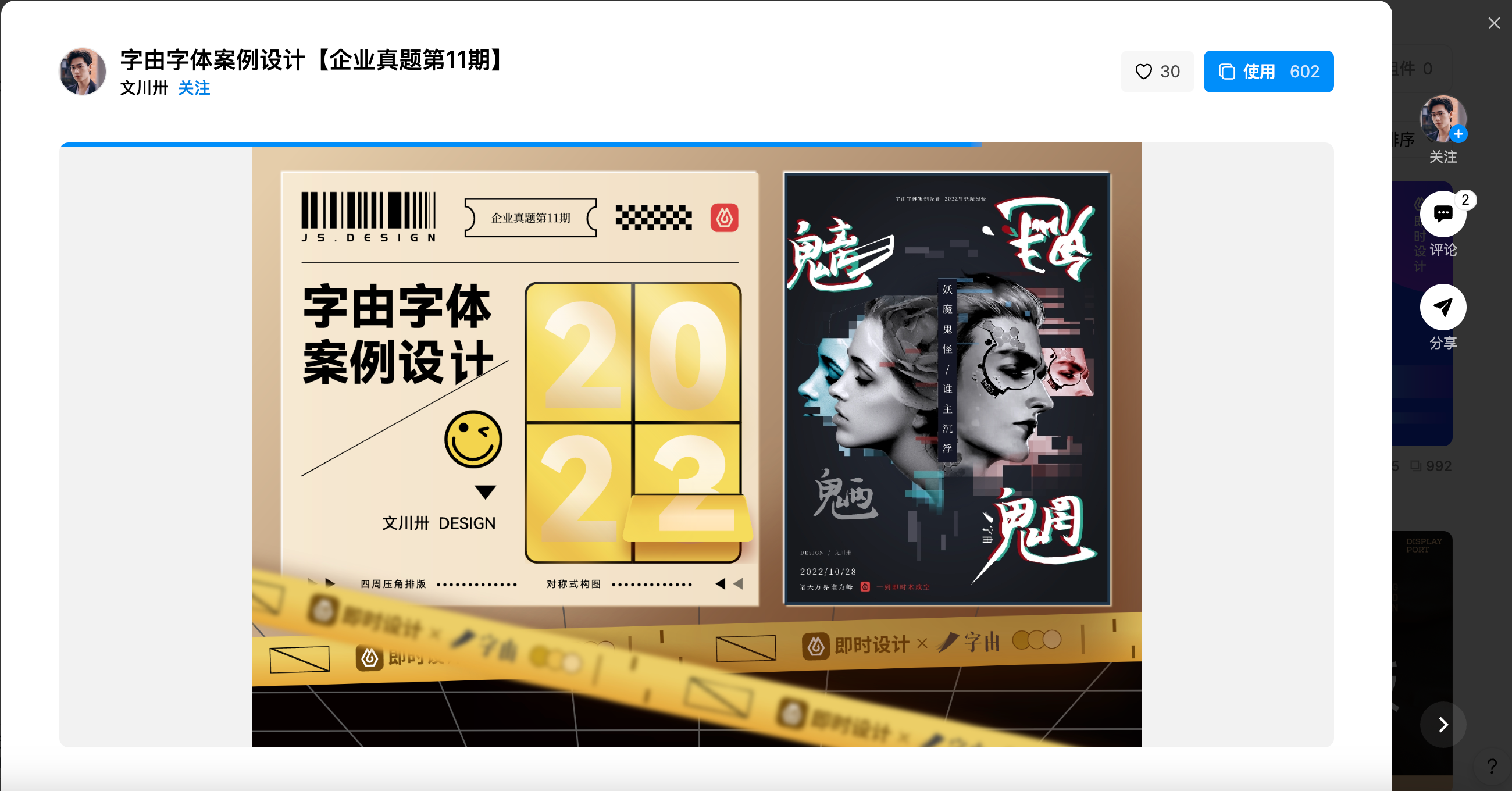
结论
字体与排版是UI设计中不可或缺的元素。通过深入了解和应用这些原则和技巧,你不仅可以提高设计的视觉效果,还可以更有效地传达信息和情感。希望本篇字体与排版的教程能为你的UI设计之路提供有用的指导和灵感。这篇文章涵盖了排版和字体选择的基础知识和实用技巧。除此之外,大家可以前往即时设计学习更多关于字体与排版的设计干货,一定会对大家有很大的帮助。